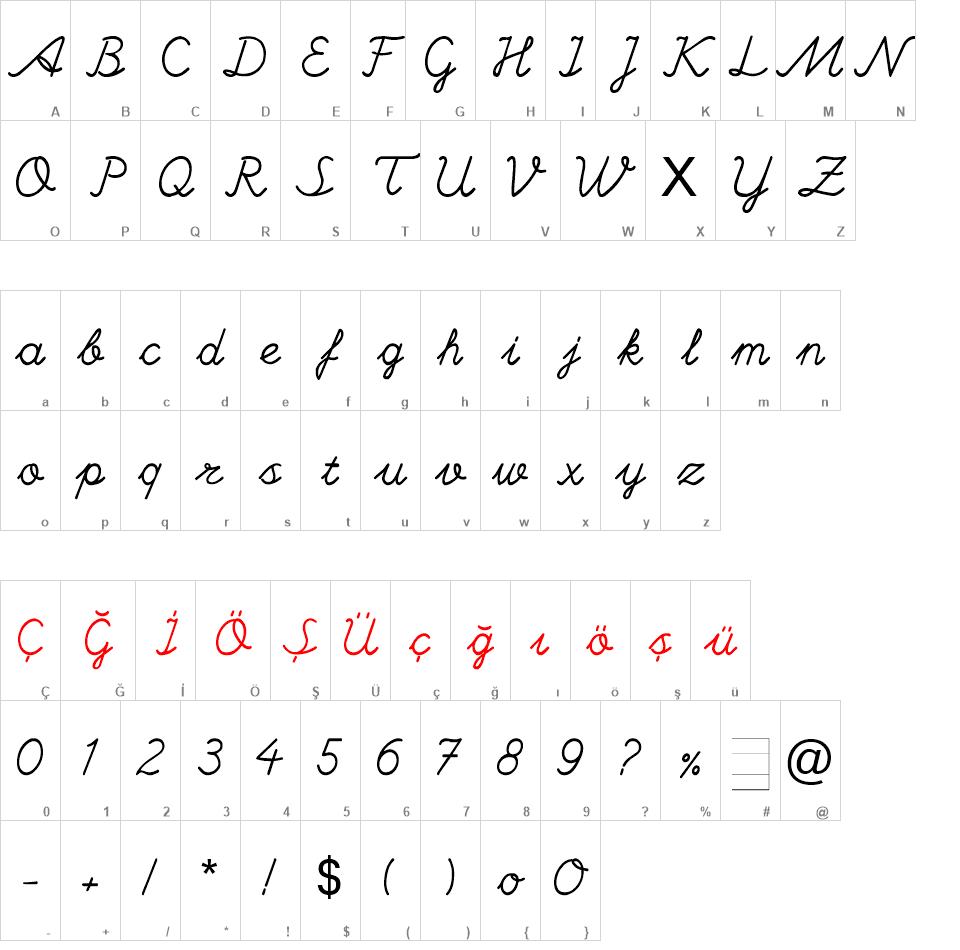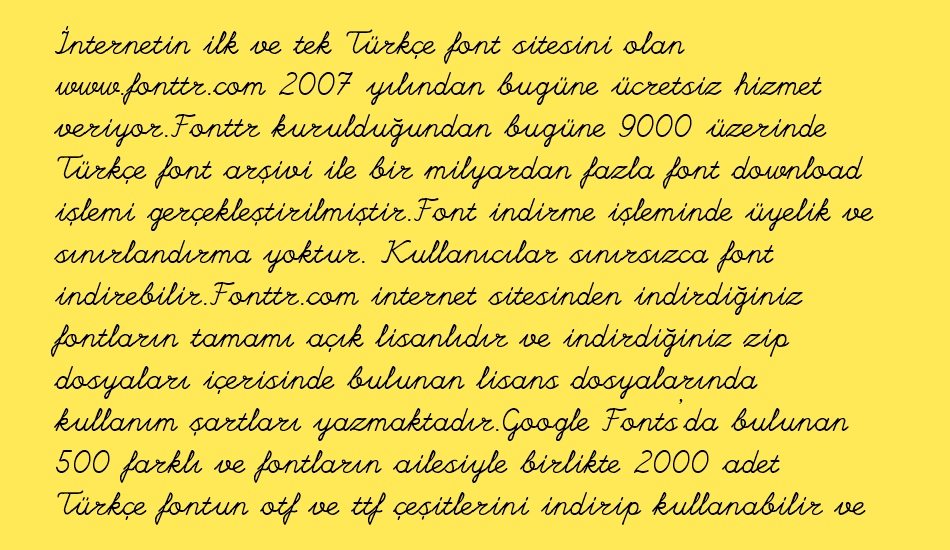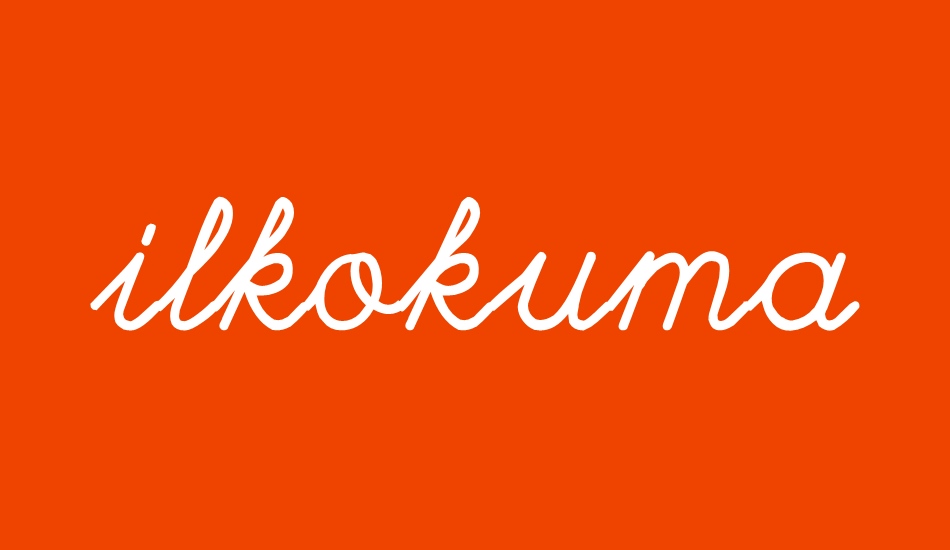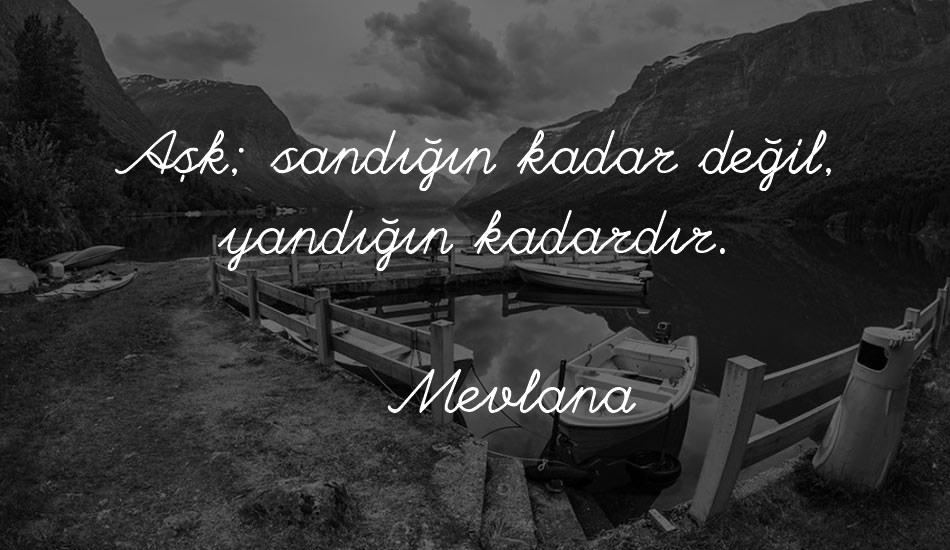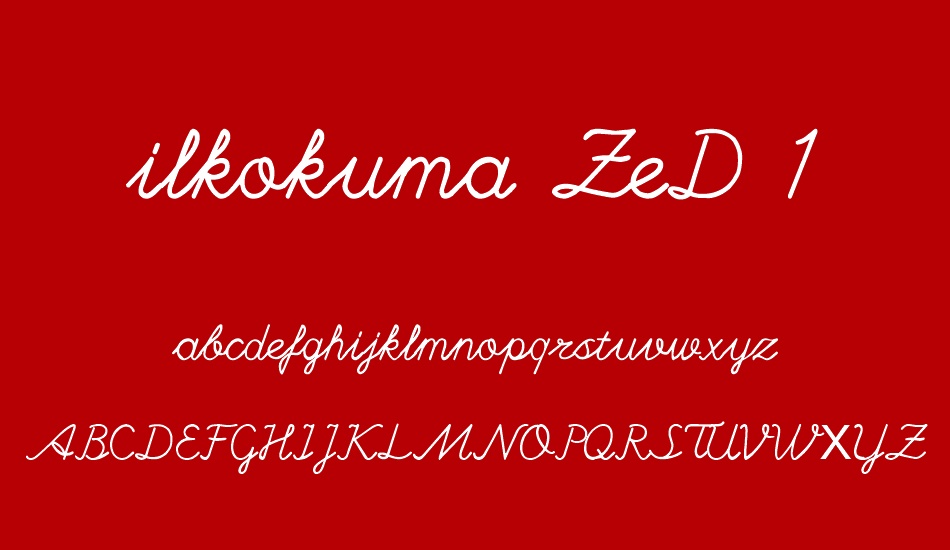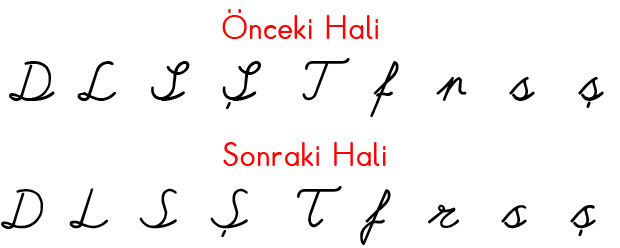
Yeni bitişik eğik el yazıu Hand Writing Mutlu font
Hand writing mutlu yeni
Bitişik eğik yazı fontu güncellendi.
Bitişik eğik yazı fontları 5 adet.
1- İlkokuma el yazısı
2- İlkokuma el yazisi yönlü
3- ilkokuma kılavuz cizgili noktalı
4- ilkokuma kılavuz cizgili sade
5- ilkokuma sade noktali
Yeni Eğik El Yazısı Fontu Hand Writing Mutlu yeni el yazısı fontu
2016 -2017 öğretim yılında Yeni Hand Writing Mutlu fontu , birleşik el yazısı font indir. Yeni el yazısı fontu indir. Yeni el yazısı harfleri 5 büyük harf ve 4 küçük harftir.